1. LITTLE BIRD: VINTAGE SCRIPT FONT
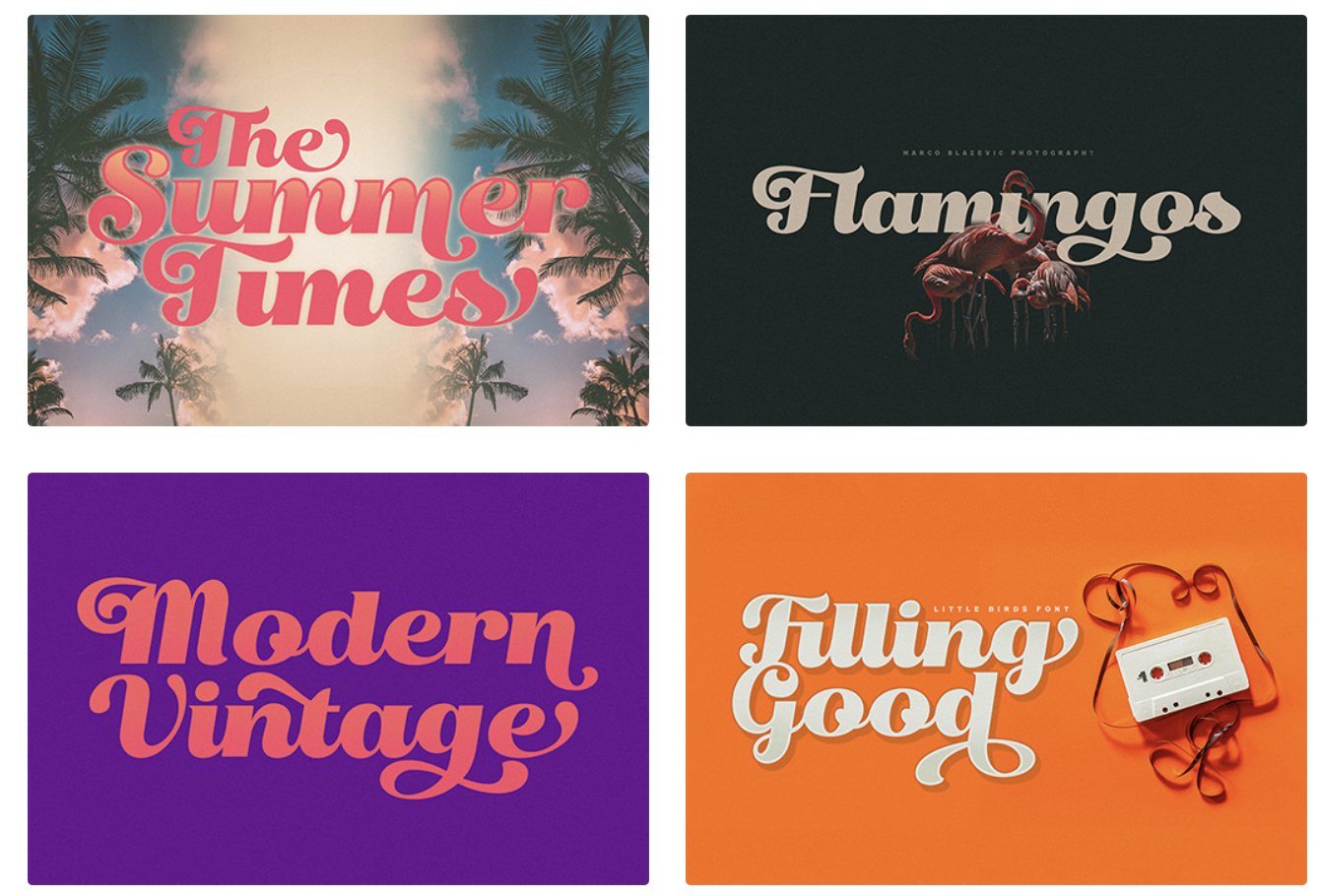
์ด๋ฐ ๋๋์ผ๋ก ํฐํธ๊ฐ ์ ์ฉ๋๋ค๊ณ ํด์
์๋ ํ๋ฉด์ฒ๋ผ ํ ์คํธ๋ ๋ด๊ฐ ๋ฐ๊ฟ์ ๋ฏธ๋ฆฌ ์ ์ฉํด๋ณด๊ณ ๊ฐ์ ธ์ฌ ์ ์์ต๋๋ค! ใ ใ
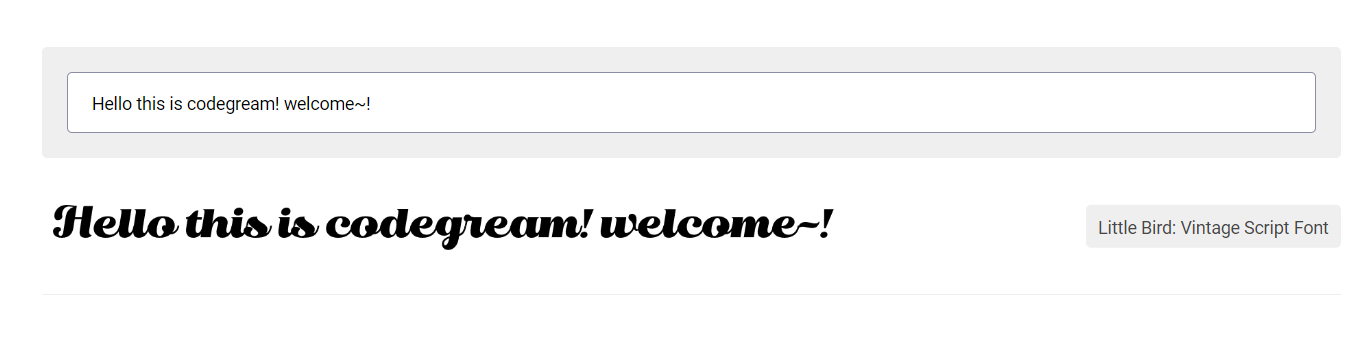
2.Fulgent - Free High Contrast Serif Font
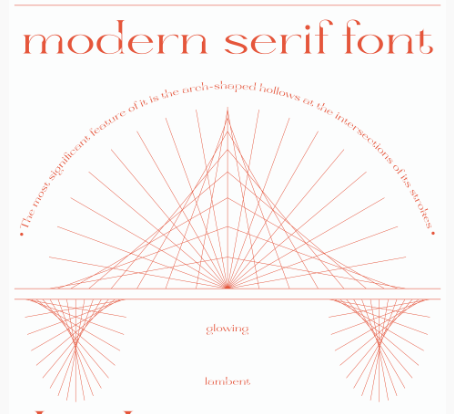
์ด๊ฑฐ๋ ๋ฐ๋ก ์ฝ์๋ก ์ ์ํ๊ฑฐ๋ ์คํฐ์ปค๋ก ์ ์ํด๋ ๋ ๊ฒ ๊ฐ์์!
๋ณด์๋ง์ ์ ์์๋ค ์๊ฐ์ด ๋ค์์ด์.๐๐
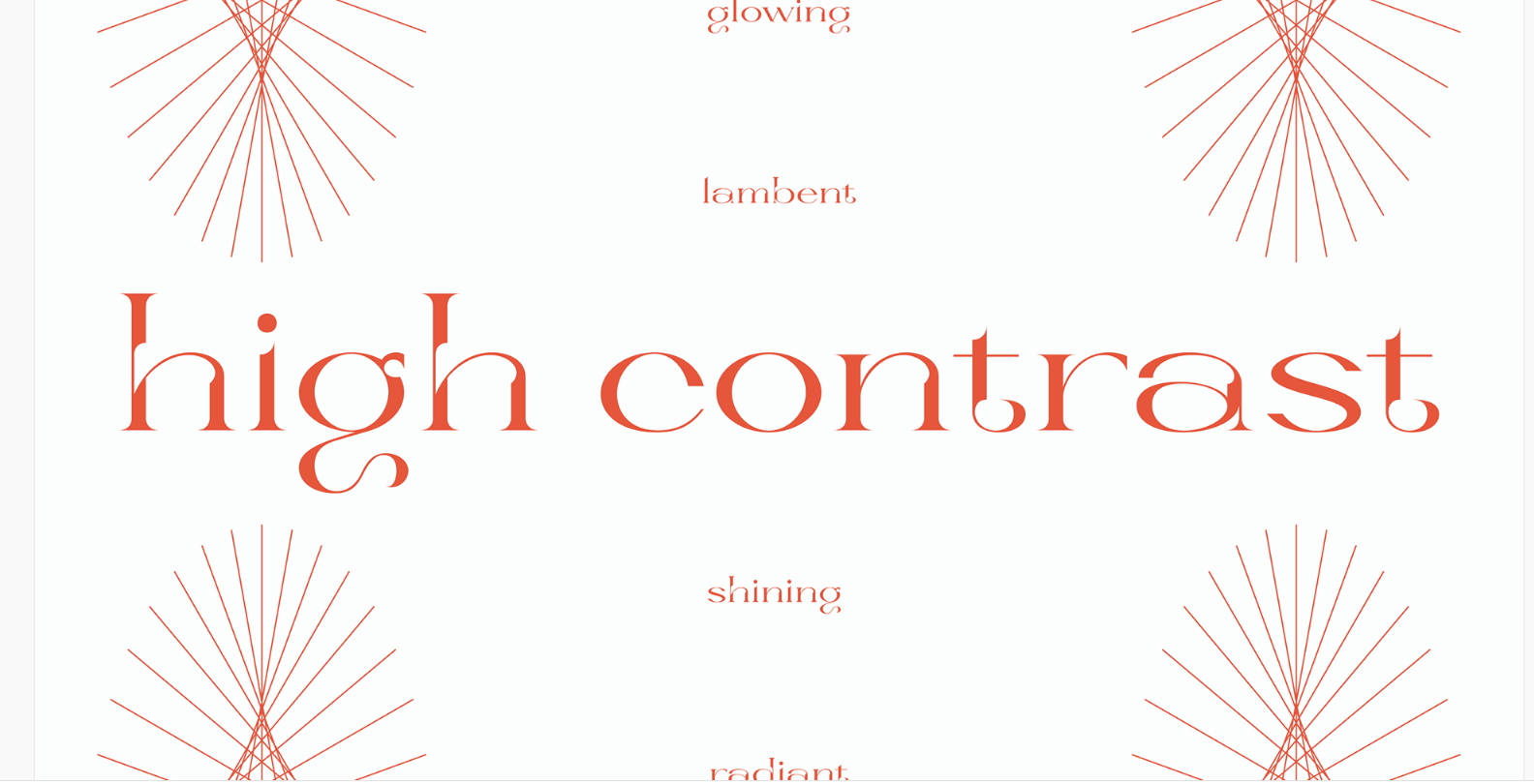
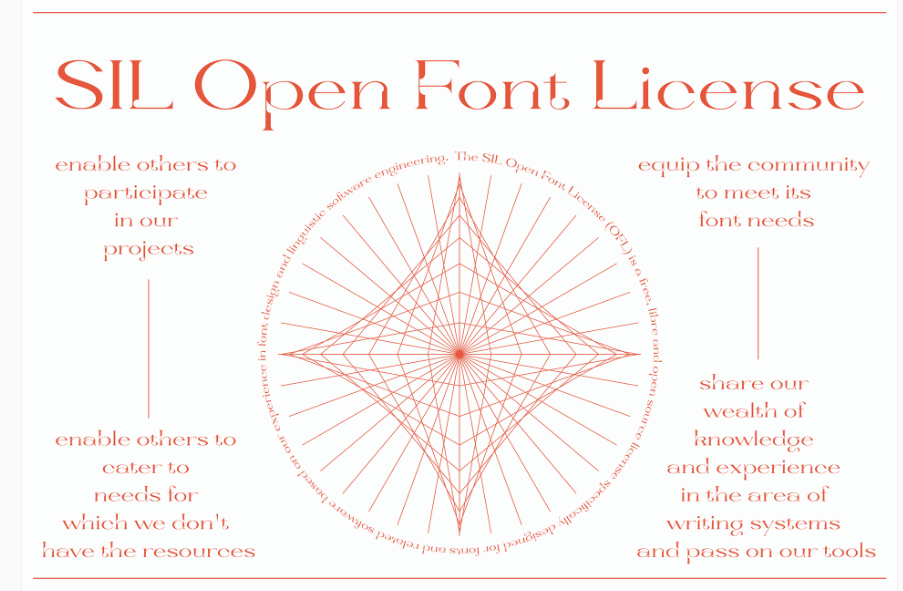
์ด๋ฐ์์ผ๋ก ์ฌ์ดํธ ์ ์์ ์ฌ์ฉ๋๋ ํฐํธ๋ง์ผ๋ก๋ ์์๋๋์ด ๋ฌผ์ฌ ๋ ๊ฒ ๊ฐ์ ํฐํธ์ ๋๋ค ใ ใ ใ
3.Clurbantik - Free basic Cyrillic/Latin font
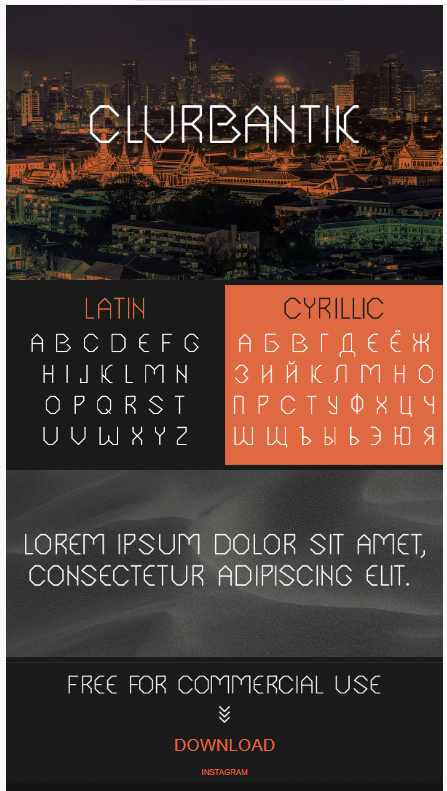
์ด๋ฒ์ ์ฝ๊ฐ ๊ฐ์ง๋ฉด์๋~ ๋ฅ๊ธํ๋ฉด์๋~ ์์~
ใ ใ ใ ใ ๊ทธ๋ฐ ํฐํธ์ ๋๋ค!
๊ฒ์์ ํ์ฉํด๋ ์ข์ ๊ฒ ๊ฐ๊ณ
๊ฑด์ถ๋ฌผ ๊ด๋ จ๋ ์ฌ์ดํธ์ ํ์ฉํด๋ ๋๋ฌด ์ข๊ฒ ๋ค์ ๐๐
4.Olegos Typeface ( Free )
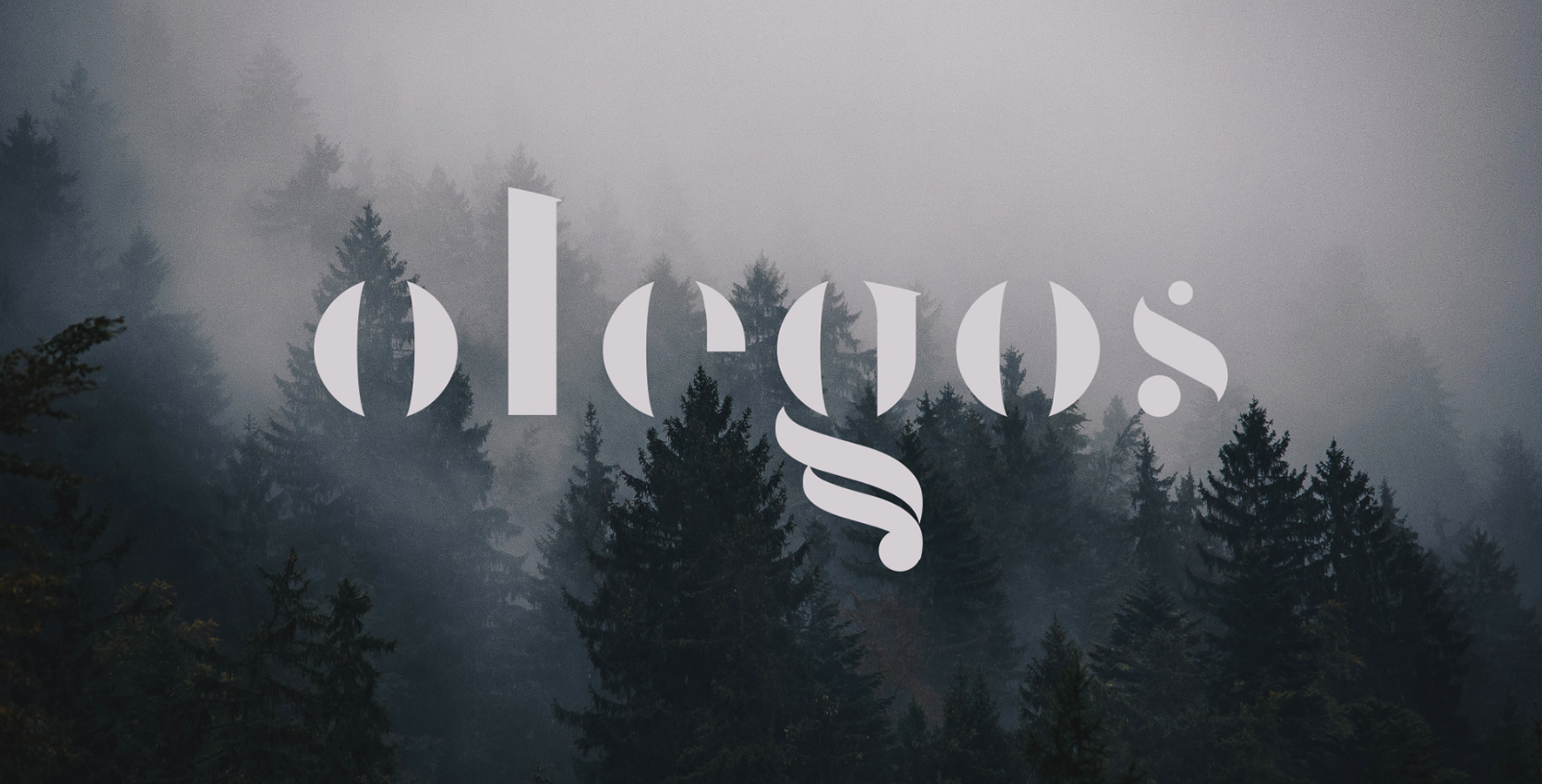
๊ณ ๊ธ์ค๋ฝ๊ณ ๊น๋ํด์ ๋ก๊ณ ๋ก ์ฐ๊ธฐ์๋ ๊ด์ฐฎ์ ํฐํธ์ธ๊ฑฐ ๊ฐ์์~
๋ฑ๋ก๋์ง ๊ฝค ๋ ํฐํธ์ธ๋ฐ ์์ง๋ ์์ฃผ ์ธ๊ธฐ๊ฐ ๋ง๋ค์ ใ ใ ๐
5.Her name is Rie (Free Font)
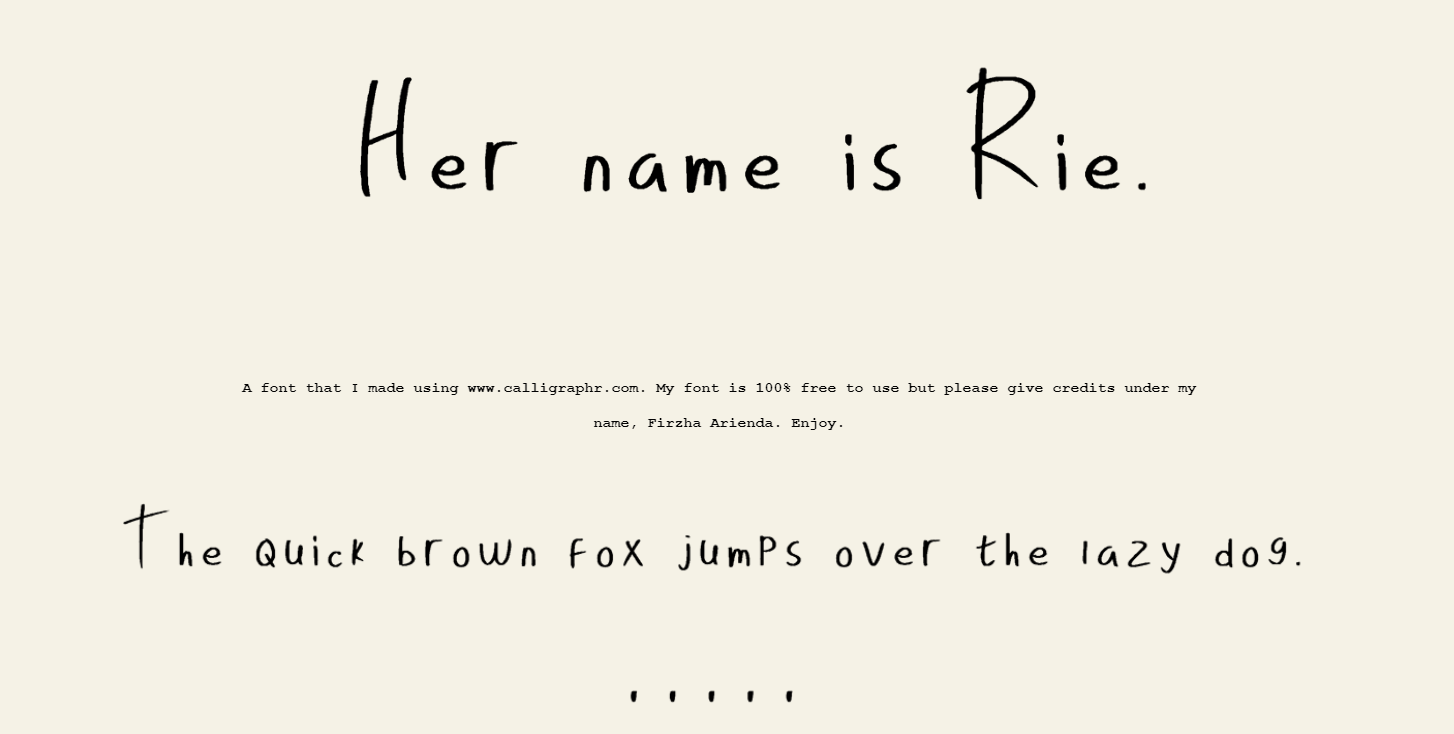
์๊ธ์จ์ฒด ๋๋, ํ๋ญ์ฒด ๋๋ ์ํ์ จ์ผ๋ฉด ์ด ํฐํธ๋ ์ ๋ง ๊ด์ฐฎ๋ค์.
๋ง์น ์๊ธ์ฌ๋ฐ? ๋ด ์๊ธ์จ๋ ์ด๋ ๊ฒ ์์๊ฒ ๋์ค์ง ์์๋
๋ฐ์๋ก ํฐํธ ์จ๋ฒ๋ฆฌ๊ธฐ~ ใ ใ ใ